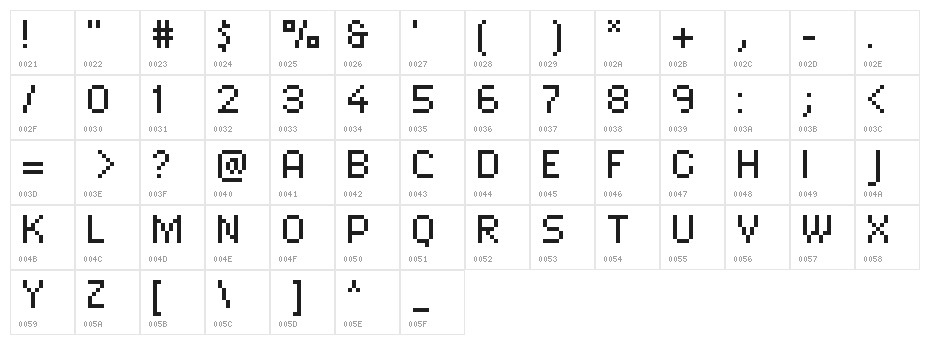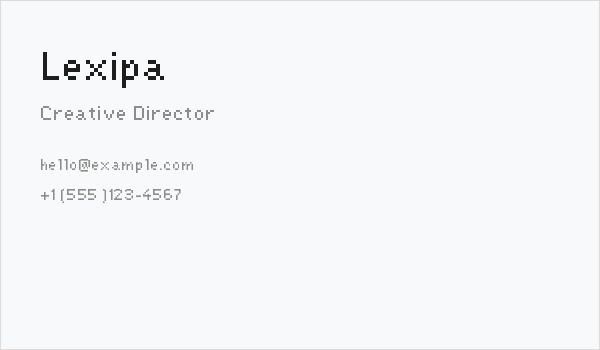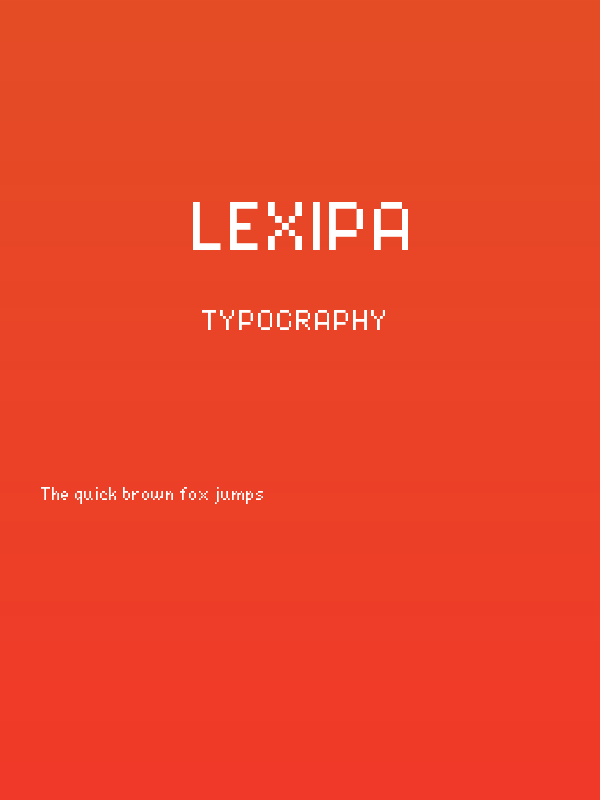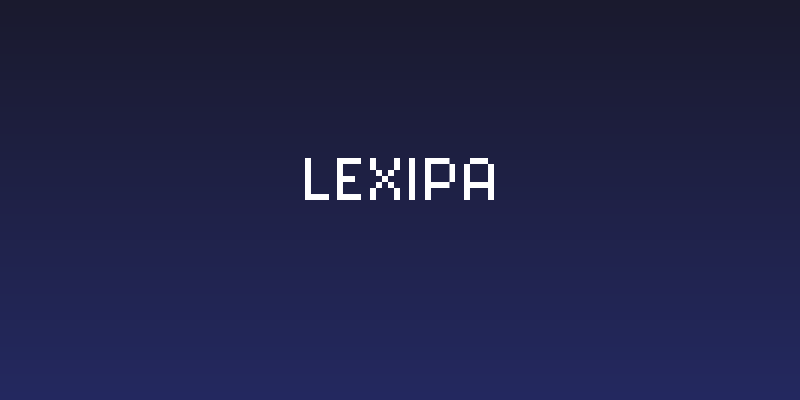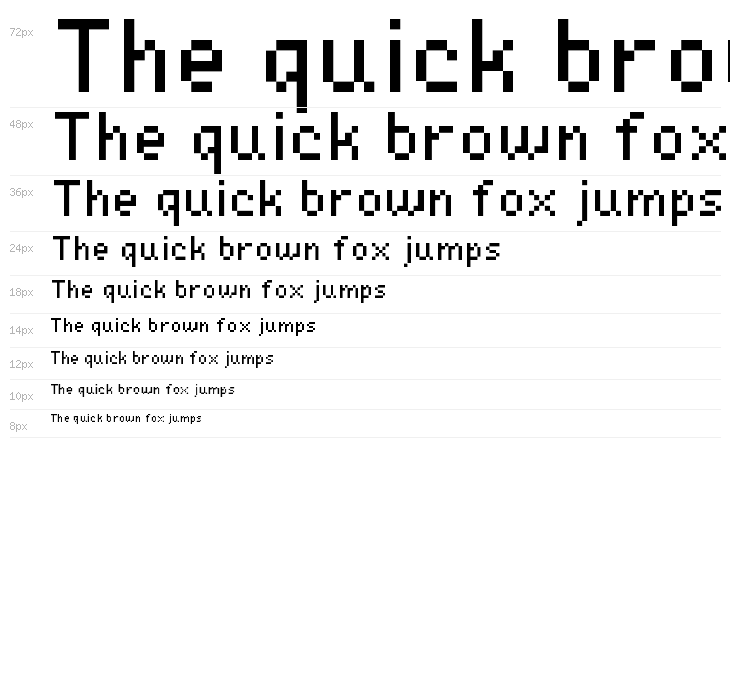
Lexipa Font
✎ Pixel
| Gesamtstil | Retro, Digital |
| Anwendungsfall | Headlines, Logos, Digital Art |
| Vorgeschlagene Projekte | Ideal for retro video game designs, digital art projects, tech-themed posters, and websites aiming for a vintage digital aesthetic. |